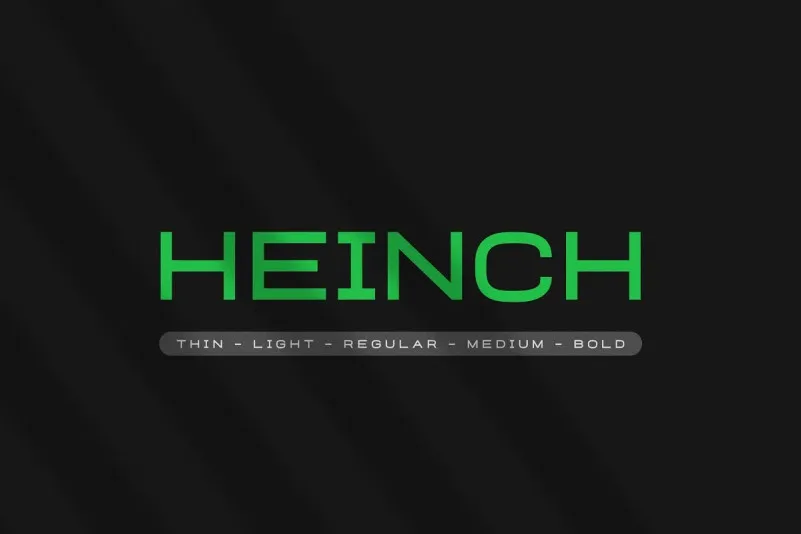
Heinch Medium é uma elegante fonte geométrica de sans-serif criada pela Almarkha Type. Inspirada nos logotipos famosos de marcas tecnológicos e nas marcas que destacam sua força característica, essa fonte oferece cinco opções para quem busca resultados satisfatórios em seus projetos. Perfeita tanto para uso em materiais promocionais como posters e embalagens, quanto para criação de logotipos e branding, Heinch é uma escolha ideal que se adapta a múltiplas necessidades. Com sua linhas diretas e formas geométricas, essa fonte moderna e sofisticada torna-se uma ótima opção para qualquer projeto que valorize um estilo minimalista e contemporâneo. Ideal tanto para designers de logotipos quanto para aqueles criando materiais promocionais ou elementos de marca, Heinch é o tipo de font que transformará seus designs em verdadeiras obras de arte.